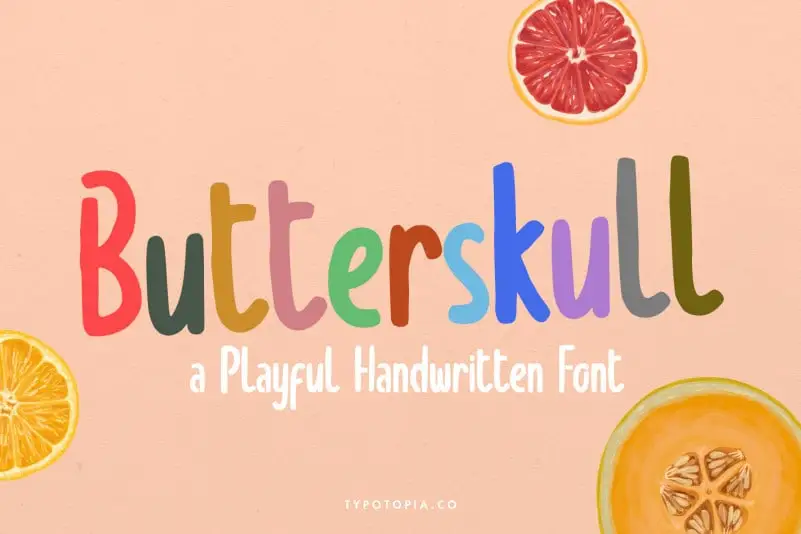
A fonte Butterskull Handwritten é uma adição fascinante ao seu acervo de letras. Introduzida recentemente, ela se destaca por sua elegância única e escrita a lápis deslizante perfeitamente adaptada para aplicação em diversos ambientes. Este tipo de letra foi projetado especificamente para uso em logotipos, moda, embalagens, menus, livros, convites, cartões de visita, embalagens, etiquetas e materiais de marketing. Ideal para quem deseja adicionar um toque autêntico e único a suas criações gráficas, esta fonte será uma opção certeira para designers que valorizam o realismo e a personalização em seus trabalhos. Sua aplicação versátil se estende de produtos fashion até cartões de convite pessoais, promovendo uma experiência visual única. Não deixe de explorar as infinitas possibilidades criativas desta fonte incrivelmente única.